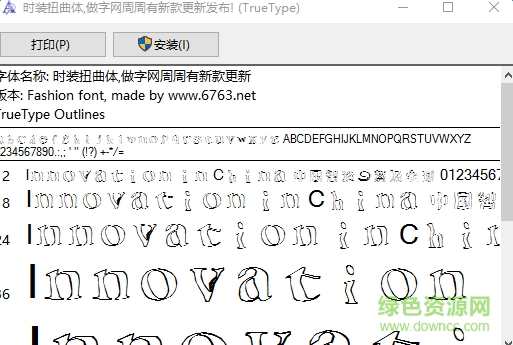
時裝扭曲體
時裝扭曲體是一款很不錯的電腦字體,這款字體寫出來的效果是很有特色的,就像它的名字所說那樣是扭曲的,是不是很特別呢,大家如果喜歡這款字體的話可以隨時來綠色資源網(wǎng)下載。
時裝扭曲體是真的很不錯,不管用于什么方面都很合適,特別是藝術(shù)設(shè)計、廣告設(shè)計等都是很不錯的,歡迎大家來綠色資源網(wǎng)下載。